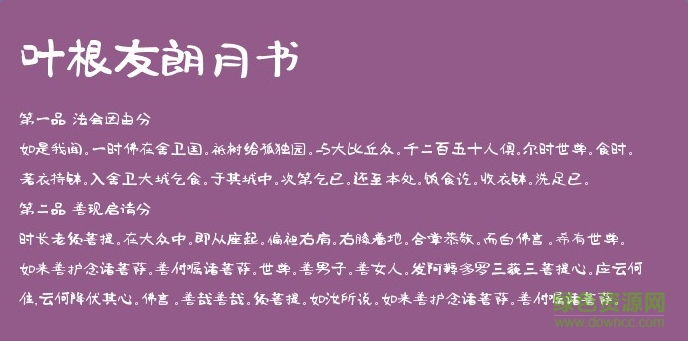
葉根友朗月書字體是一款休閑文雅風(fēng)格字體軟件,朗月書體筆畫以手寫為主,創(chuàng)意十足,十分俏皮,非常受年輕人的熱愛與追捧,還有更多好看字體歡迎來綠色資源網(wǎng)下載體驗!
葉根友朗月書字體根據(jù)葉根友手寫體制作,該字體自然灑脫,看起來左暈右倒但是卻不是凌亂,而是一種過渡的唯美!
該字體筆畫隨意自然,看似灑脫放蕩不羈,卻不失工整,非常有韻味,在印刷廣告字體設(shè)計方面有著不錯的應(yīng)用,創(chuàng)意十足,值得收藏使用!